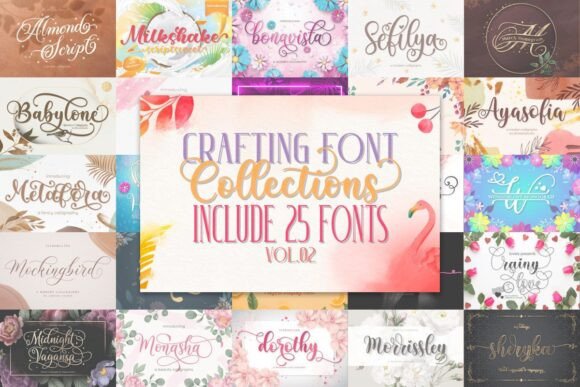
Crafting Font Bundle Vol.02
Doğru tasarım öğelerini bulmak zor olabilir, ancak Crafting Font Bundle Vol.02, çalışmanızı anında bir üst seviyeye taşıyan olağanüstü bir koleksiyon sunar.
İster İsteğe Bağlı Baskı (POD) ürünleri, ister düğün davetiyeleri veya sosyal medya grafikleri oluşturuyor olun, Crafting Font Bundle Vol.02 ideal bir uyumdur.